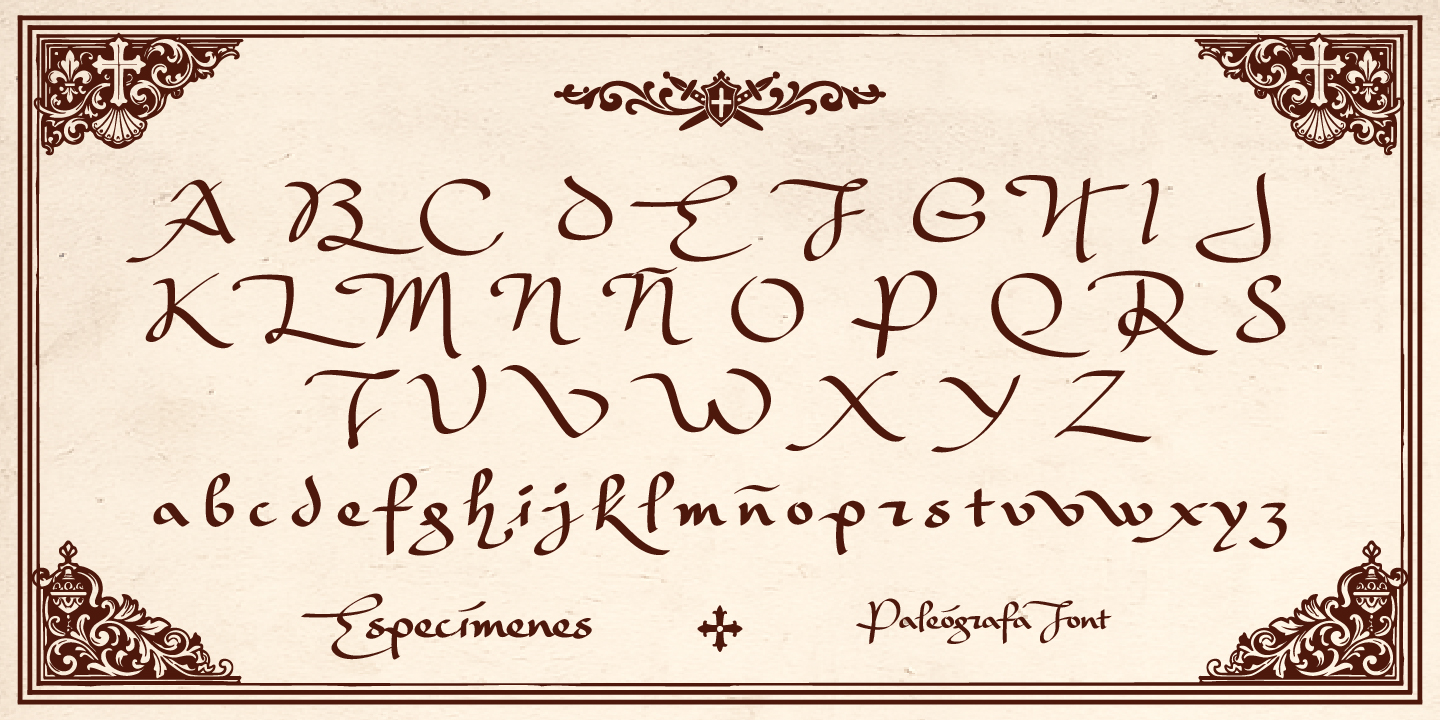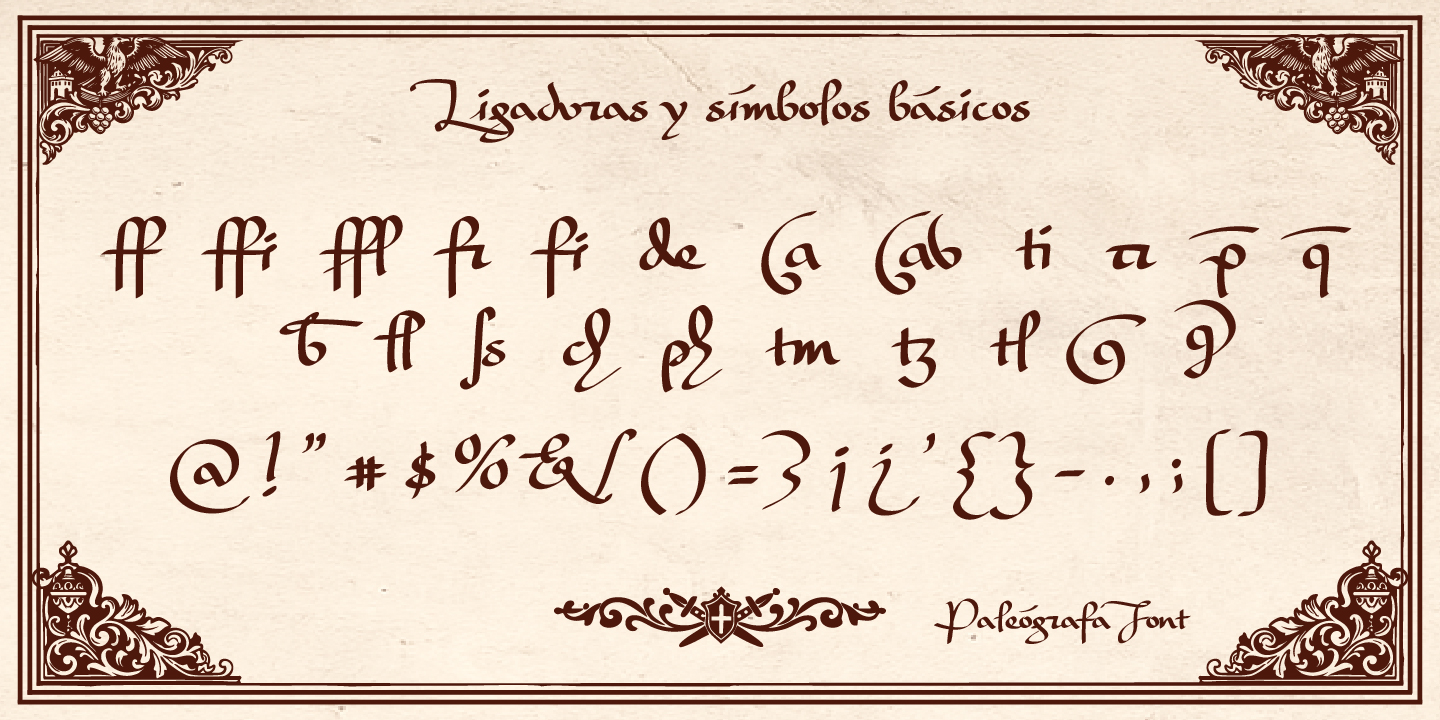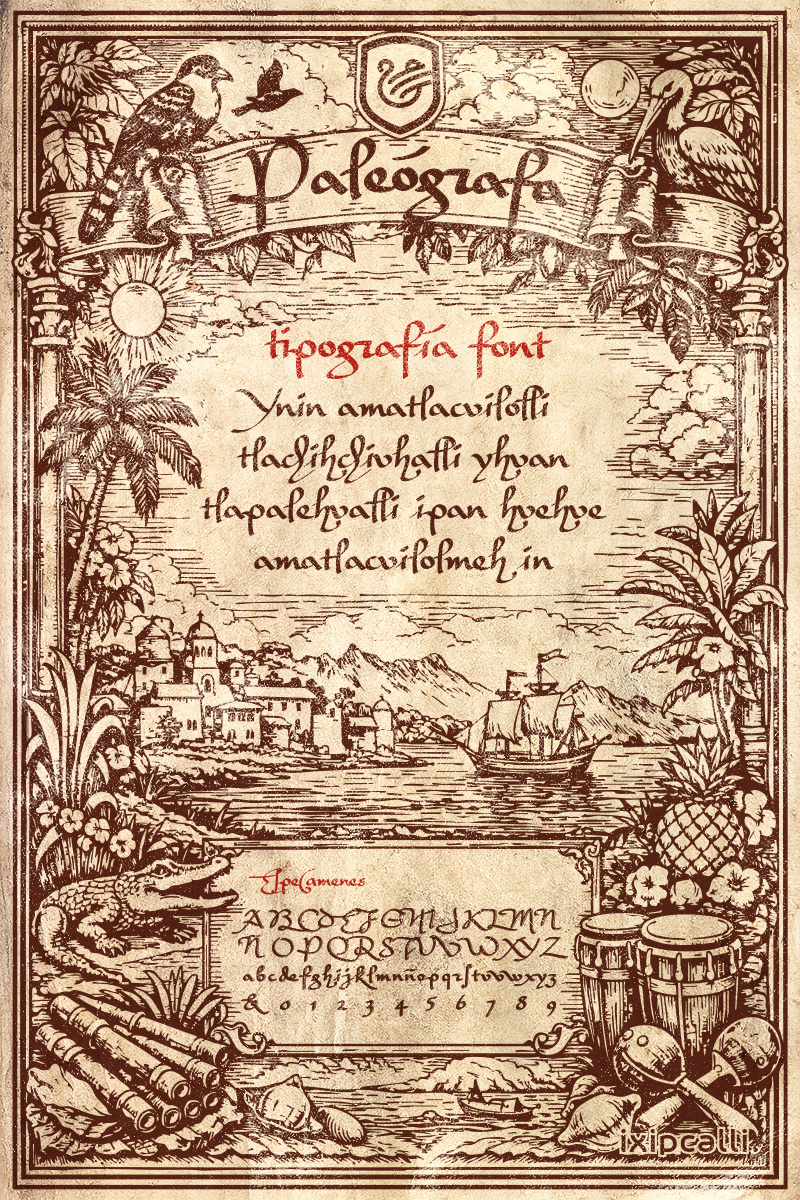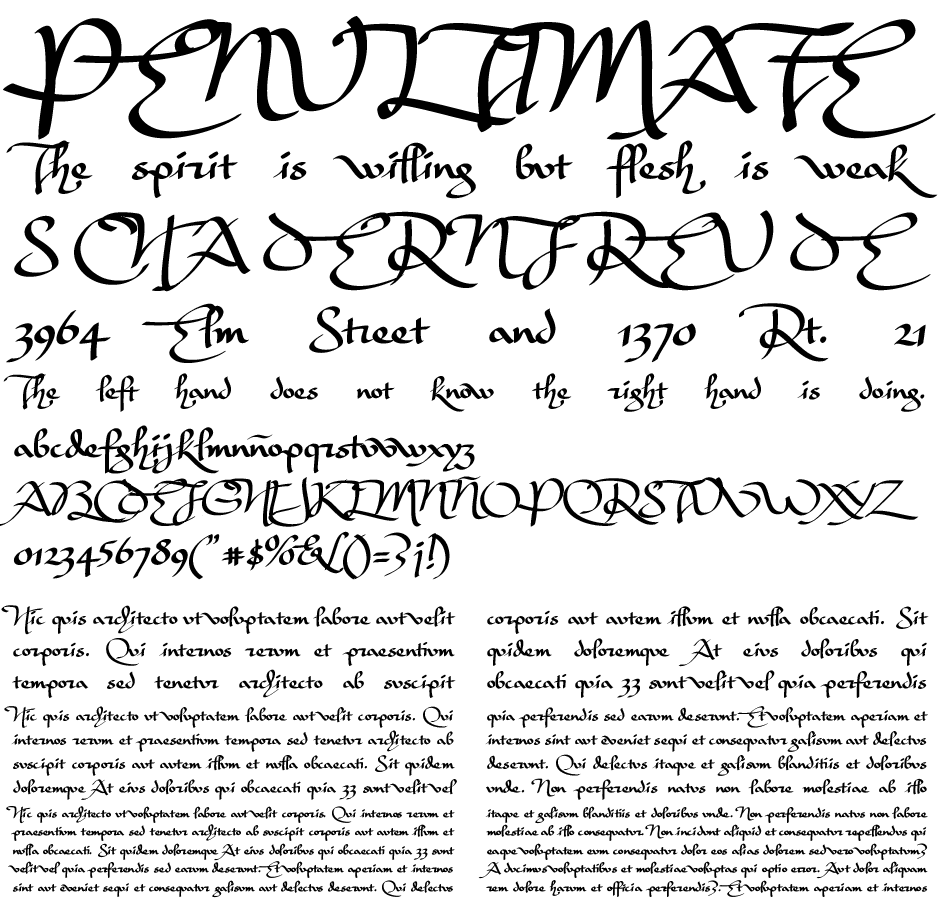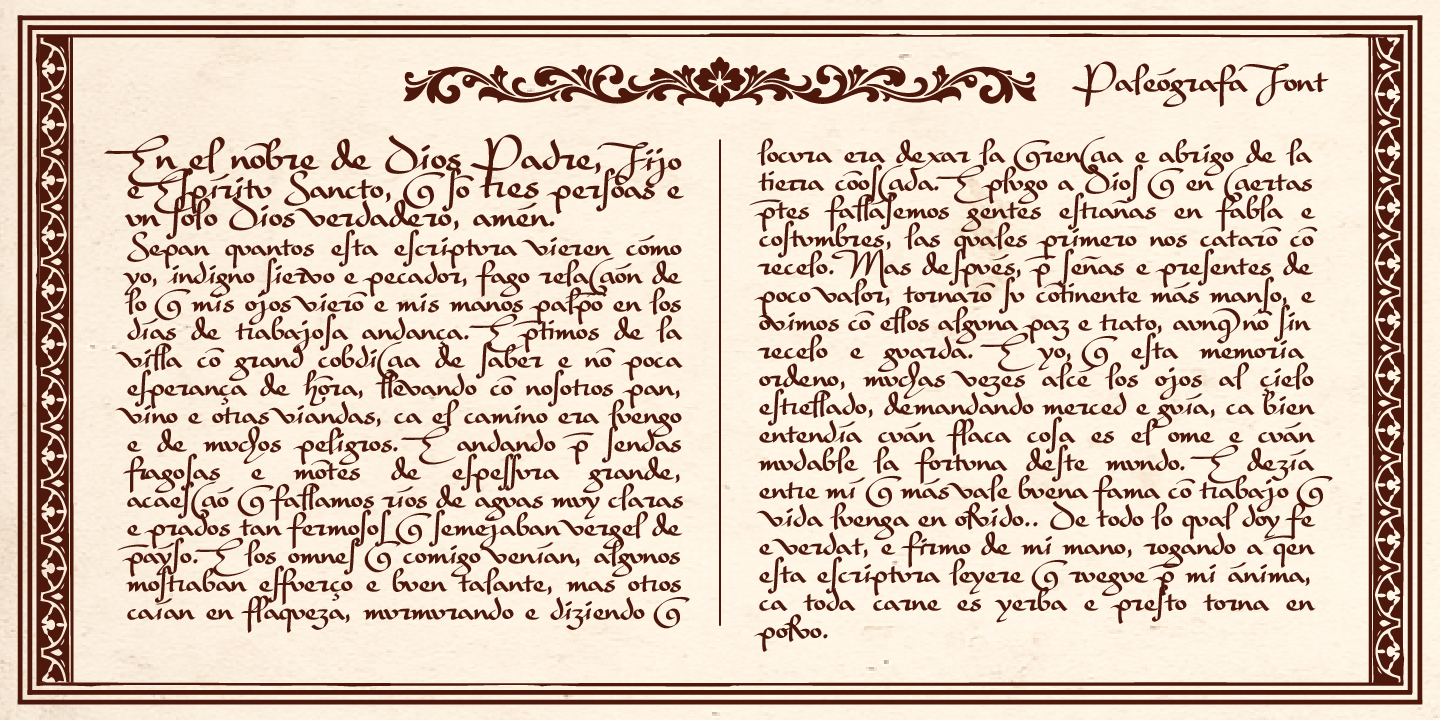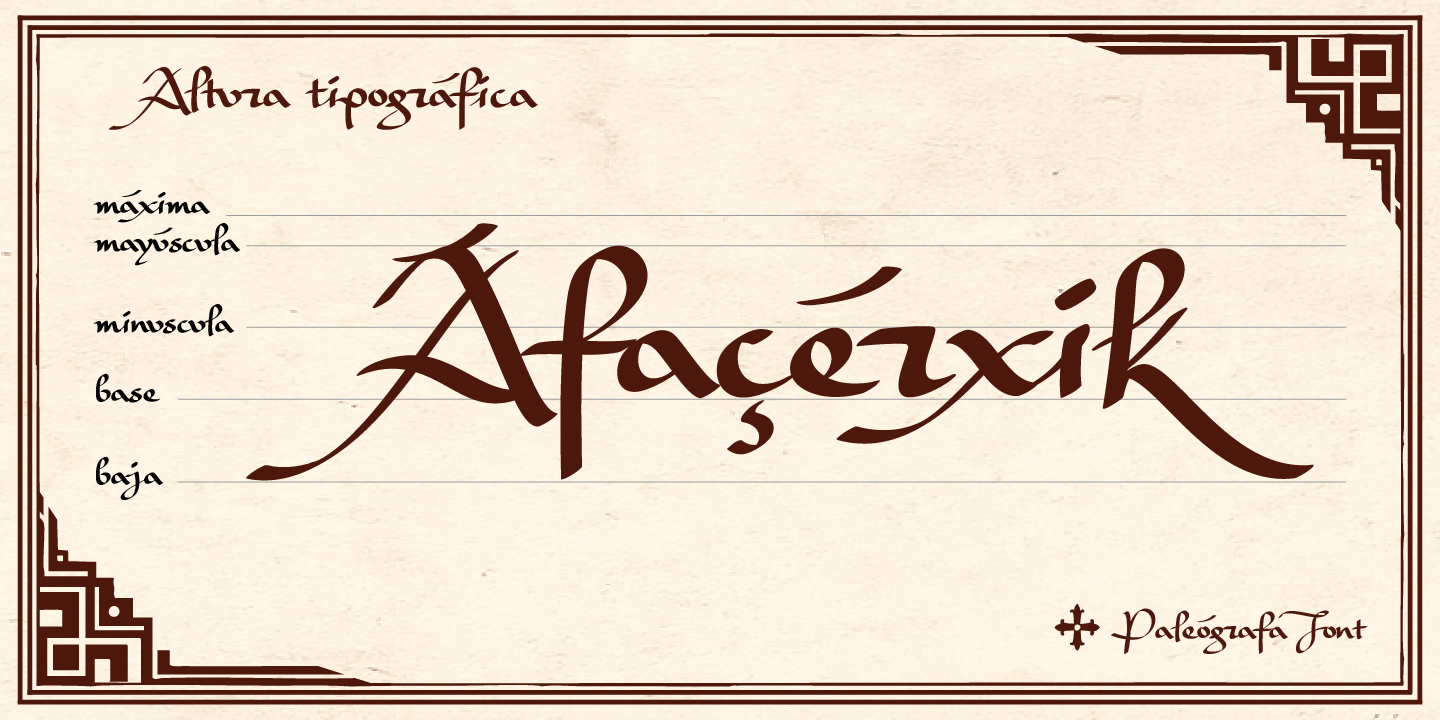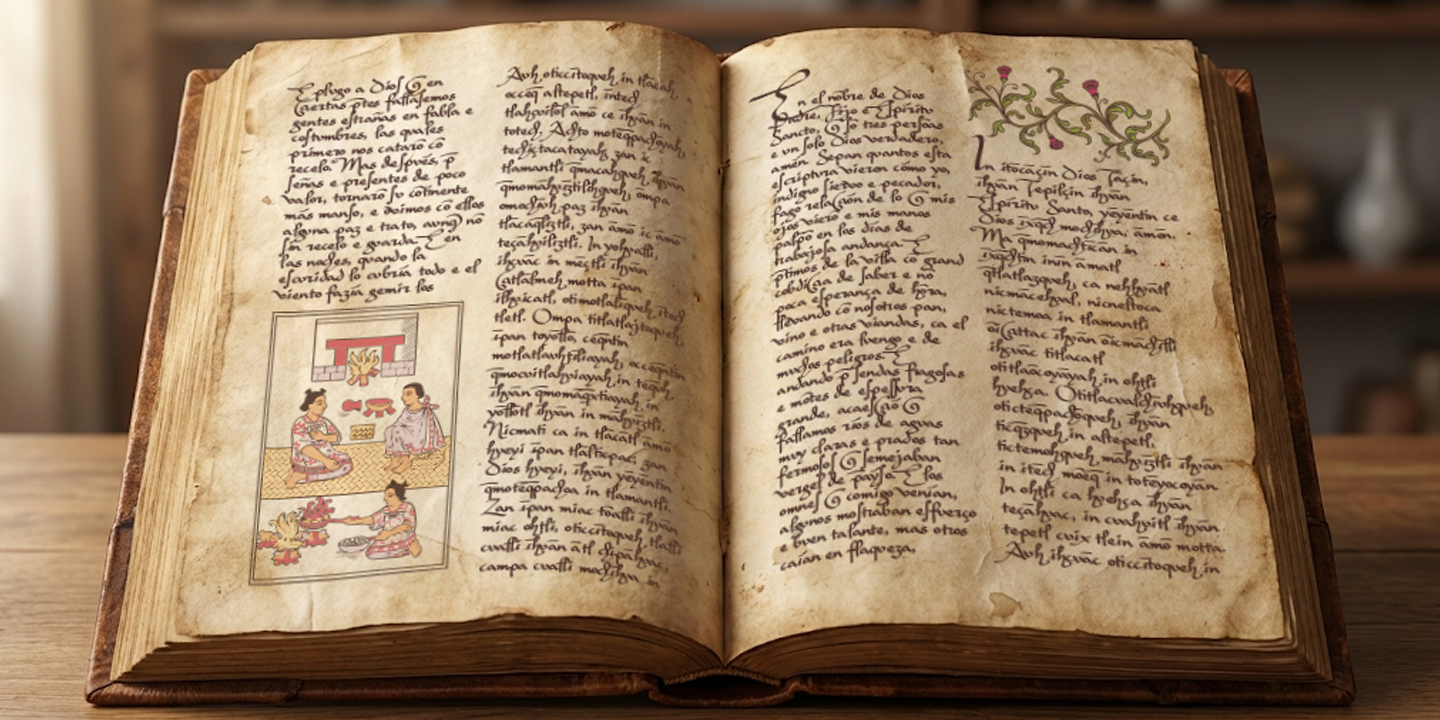
paleografa
Descripción
(2026) - Paleógrafa es una tipografía de inspiración paleográfica que evoca la riqueza visual de los manuscritos antiguos. Su trazo orgánico y cuidadosamente irregular reproduce la textura viva de la escritura hecha a mano, conservando detalles propios de la tradición colonial y de los textos históricos de los siglos XV y XVI. Diseñada para proyectos editoriales, académicos y artísticos. Aporta autenticidad y carácter, equilibrando fidelidad histórica con legibilidad contemporánea. Esta tipografía fue creada exclusivamente para una marca de diseñador de moda.